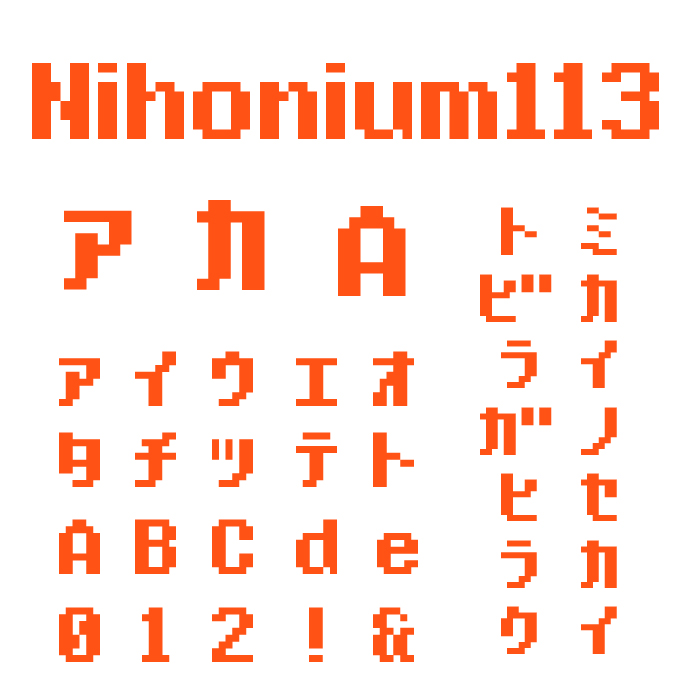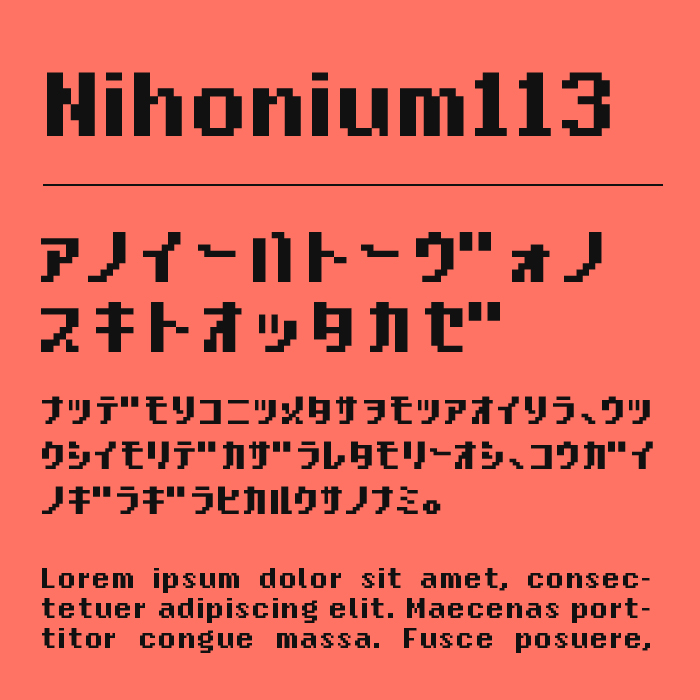
Nihonium113(ニホニウム113)フォントは、ピクセル調の骨格にほどよい角丸と重心の安定感があり、初代iPodのような、かわいらしいドットフォントフォントです。
ゲームのロゴやサウンドノベルのタイトルにも使えそうな、どこか懐かしいレトロデジタル感があります。小さなドットで構成された文字が、素朴ながら芯のある印象を与えます。
見た目に反して視認性が高く、文字が小さくても読みやすいのが特徴です。近未来感とレトロ感を融合させたい場面にぴったりで、SFテイストやドットアート風のデザインと組み合わせれば、ユニークな演出できそうなフォントです。
フォントの文字見本
収録文字は、カタカナ・アルファベット・数字・記号が収録。